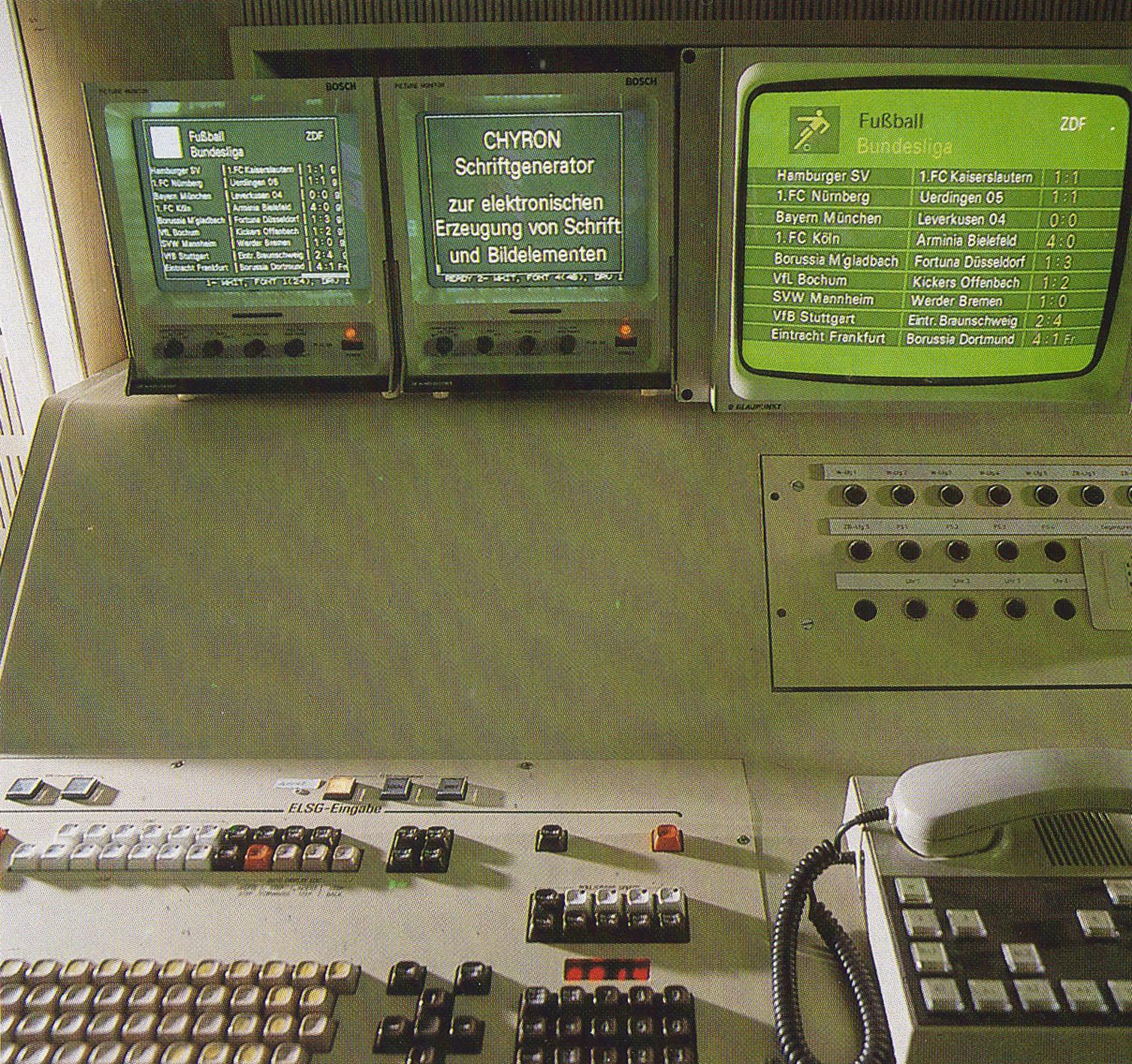
Digitalisierung der ZDF-Hausschrift
Wer ist imstande, mir nach Vorlage die damalige ZDF-Hausschrift von Otl Aicher (nach Inspiration der UNIVERS von Adrian Frutiger) zu digitalisieren,
Anbei Vorlagen.
Gibts doch bestimmt schon irgendwo. Auf die Schnelle hab ich zumindest einige Schnitte gefunden...